【井関農機】トラクタ操作端末×UDフォント。現代的な佇まいのフォントがもたらした、ディスプレイの「進化」
井関農機株式会社様は、1926年、愛媛・松山の地で創業された農業機械の総合専業メーカーです。創業者・井関邦三郎氏の「農家を過酷な労働から解放したい」という理念の下、トラクタやコンバインなど農作物の生産に関わる製品やサービスを長らく展開し、近年では自動運転型のロボット農機を発売するなど、農業領域への更なる貢献を目指しています。
そんな井関農機様のトラクタ操作端末「IMLT®」(ISEKI Machine Link Terminal)に、弊社フォント「UD角ゴ_ラージ」を2018年にご採用頂きました。今回は、実際にフォントの選定や採用に関わられた井関農機の鈴木さんに「UD角ゴ_ラージ」をご採用頂いた理由、今後の事業展望などについて、オンラインにてお話を伺いました。
1991年福井県生まれ。静岡文化芸術大学でプロダクトデザインを専攻。大学卒業後、新卒で井関農機株式会社に入社し、デザイン部に配属。現在は、主に農業機械のプロダクトデザイン、UIデザインを担当。
厳しい環境で使用される農業機械には「直線的でメリハリのある文字」を選択
鈴木さん:井関農機のデザイン部では、自社開発の製品に関わるデザイン全般を行っています。デザイン部の作業としては、製品に使用する文字やロゴデザインや製品のカラーリング、外観デザインを考えるときのスケッチであったり、3Dデータの作成、そして操作画面液晶系のUIデザインなどを主に行っています。特に分野を区切るわけではなく全員が満遍なく作業をこなしています。
また、新製品の開発の際にはデザイン担当者が数名アサインされて、そのメンバーで全てのデザインを行うというのが弊社のデザイン部の特長です。
―― 御社デザイン部での文字(フォント)の扱いについて、もう少し詳しく教えてください。
鈴木さん:製品のイメージに合わせて、デザイナーが手作りしています。例えば、フォントサービス「LETS」の中から雰囲気が良いフォントを選択する。でも、農機向けにデザインを全く弄らなくてよいフォントはなかなか無いので、製品のイメージに合わせて常に微調整しています。
―― 「農機向けにデザインを全く弄らなくてよいフォントはなかなか無い」と頂きましたが、あらゆる天候、シチュエーションに適応する必要がある農機ならではの文字(フォント)の選択や方向性はあるのでしょうか?
鈴木さん:農機は厳しい環境で使用される製品ですので、直線的でメリハリのある文字に調整していくことが多いですね。文字自体を太くする、立体にする、側面に表示されるデカールは斜体にする、といった具合です。実際の使用環境を想定したり、我々デザイナーも農業現場でのフィールドワークを通じて着想を得たりするなどのプロセスを経て、製品に表示される文字ができ上がっていきます。
私も、直近ではミニ耕うん機「マイペット KCR7シリーズ」のデザインを担当したのですが、この製品のフォントは「Monotype LETS」に収録のEurostile®を採用しました。このEurostile®は、まさに直線的でメリハリのある欧文フォントで、ウエイトのバリエーションも豊富、個人的にも非常に好みですね。
自身の感性に響いた「UD角ゴ_ラージ」。農家のお客様にも伝わる、その心地よさ
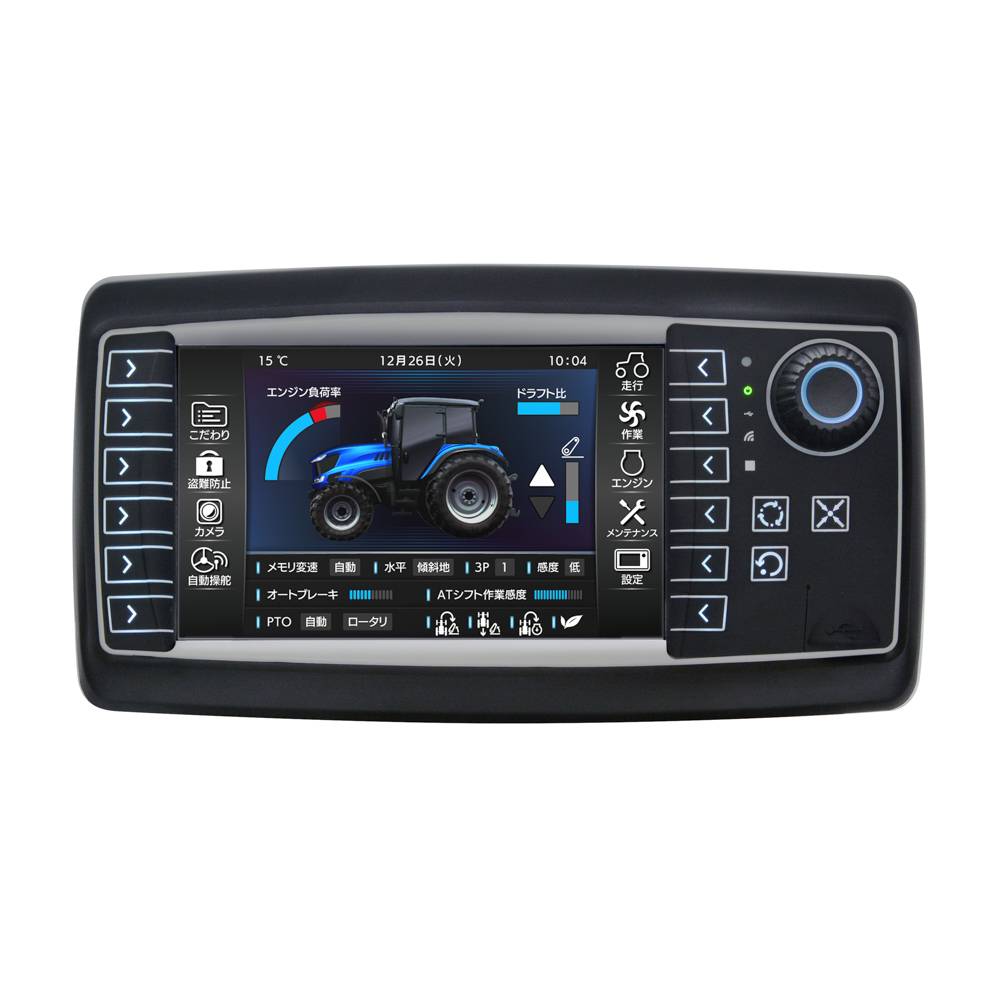
―― さて、今改めて「IMLT®」で弊社のユニバーサルデザインフォント「UD角ゴ_ラージ」をご採用頂いたプロセスを振り返って頂けますでしょうか。
鈴木さん:当初トラクタ操作端末「IMLT®」の使い方として、運転時に画面を一瞬だけ確認することを想定していました。そのため、瞬時に情報を正しく伝えられるフォントが必要でした。また、7 インチの画面に可能な限り多くの情報を表示したいという必要性もでてきたため、次第にUD フォントの優位性が高まってきました。さらにトラクタ操作端末に表示するためには組み込みフォントでなくてはならないことが分かり、弊社ではトラクタ操作端末への組み込みフォント搭載が初めての経験でしたので、いろいろと手探りで探して、当時数社のフォントメーカーに相談させて頂きました。
―― 他のフォントメーカー様にもご相談されていた中で、弊社をご選択頂いた理由はどこにあるのでしょうか?
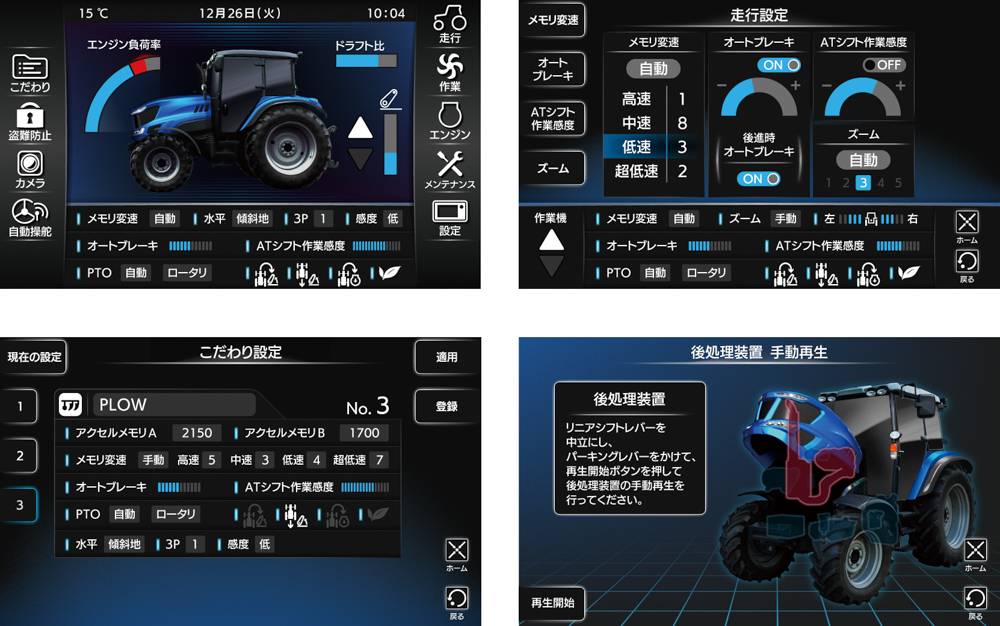
―― 御社のご希望に寄り添えたことは嬉しい限りです!ここからは、フォントのデザイン視点でお話を伺いたいと思います。先ずは、ユニバーサルデザイン(UD)のコンセプトを持ったフォント自体はご存知でしたでしょうか?
鈴木さん:ユニバーサルデザイン(UD)フォントの存在自体は認識していました。例えば、弊社の印刷物などで他社のUDフォントを実際に使用していました。
―― 既に他のフォントメーカー様のUDフォントを使用されていたなかで、弊社の「UD角ゴ_ラージ」をご採用頂いた理由はどこにあるのでしょうか?
鈴木さん:(トラクタ操作端末の)ディスプレイの解像度は、実はそこまで高精度なものではないんです。ディスプレイでは文字が荒れることが多い中で、「UD角ゴ_ラージ」は綺麗にはっきり見えるところが良いなと感じました。文字がしっかり読めるからこそ、ディスプレイに情報をより多く表示することができます。ふところが広く、曲線も美しいといった現代的な佇まいを感じさせながら、「分かりやすくて格好良い」という社内の評判が最後の決め手となりました。
―― UDフォントの基本的な特長である「可読性」「視認性」「判別性」の高さに加えて、弊社独自の観点である「美感性」を備えた「UD角ゴ_ラージ」の本質を見事に捉えて頂いています!
鈴木さん:フォントメーカー数社からフォントをお借りして、ディスプレイに表示して検証を行ったときに、「UD角ゴ_ラージ」を打ち込んで「これいい!」と(笑)。自身の感性に響きましたね。フォントそのものに心地よさと親しみやすさがあるため、お客様にもその心地よさは伝わっているだろうと感じています。
変化の大きい農業の世界を「骨太で息の長いデザイン」で支えたい!
―― 御社も2025年に創立100周年を迎えられますが、農業の世界も最近は特に大きく変貌を遂げているとお伺いしています。農業の世界で、いまどのような変化が起こっているのでしょうか?
鈴木さん:前提として、お客様が先ず変化していってますね。日本国内においては、農業従事者の高齢化が一層加速しています。それを背景に、農地の集約・大規模化がトレンドとなっており、そのプロセスで担い手農家と言われる若手や法人も多く参入してきています。
技術面に目を向けると、農業就業人口の減少に伴う作業の効率化・省力化でしょうか。具体的には、大規模経営ではAIやデータを活用したスマート農業が盛んになってきています。例えば、人が見回る代わりにドローンを飛ばして、撮影した画像の色から稲の生育具合をAIが判断して、水や肥料を調整する手法や、人工衛星の画像からお米の味の決め手であるタンパク質含有量を把握して、最適な収穫時期を決定する手法が普及レベルにきています。農業のやり方自体が大きく変わってきていることを感じます。
―― なるほど。因みに、御社のこの領域における最新の取り組みを教えてください。
鈴木さん:弊社では「可変施肥田植機」を販売しております。肥料を撒きながら田植えをするのが一般的になってきていますが、「可変施肥田植機」はリアルタイムセンシング技術で土壌の肥沃度合いを調べ、肥料を田んぼのどこにどれくらい撒くか最適化しながら田植えをします。そうすることで稲の倒伏を防ぎ、品質の安定したおいしいお米になります。
―― ご教示ありがとうございます。最後に、農業を取り巻く環境の変化に適応され、業界のフロントランナーとして走り続ける御社のデザイナーとして、鈴木さんの「矜持」をお聞かせください!
鈴木さん:農機は何十年と使い続けて下さるお客様も多くいらっしゃいますので、「骨太で息の長いデザイン」を常に心がけています。農機の世界でも新しい機能や操作が次々に出てきますが、特にUIデザインにおいては、見た目にしても、操作感にしても素直に入ってくるもの、本当に使いやすいと言っていただけるものを作り続けたい。これからも農業と農家のお客様に寄り添って、お客様の未来が広がるような製品を作り続けていきたいですね。
今回、取材を進めて行く中で、鈴木さんがプロダクトデザイナーを目指した「原点」をお伺いしました。
原体験として、福井の実家に田んぼがあり、農機具に触れる機会が身近に有ったとのこと。鈴木さんが幼い頃、農業に携わっていたおじいさんが田植えをしているときに「何となくワクワクしながら」田植機に触れていたことが、ずっと記憶に残っていたそうです。
幼少の頃は漫画を描くのが好きだった少年が、高校生の頃には工業製品のデザインに興味を抱き、静岡の大学でプロダクトデザインを専攻。就職活動では農機メーカーに絞って活動を続け、井関農機様に入社したという、大変興味深いお話を聞くことが出来ました。
「身近な人で農機メーカーに行った人は誰もいないし、誰もいないところで新しいことにチャレンジしたかった」(鈴木さん)
自身の感覚に忠実に従い、就職するまで一度も訪れたことのなかった四国の企業での挑戦を決めた鈴木さん。その飄々とした雰囲気とは裏腹に、確固たる芯を持ったプロダクトデザイナーであることを再認識させられました。
「新しい道具があると、生活がより便利になるし、豊かになるという価値の提供が出来る。新しいプロダクトをどんどん生み出し、それを使いやすくて魅力的なものに仕上げていくところで活躍していきたい」と語る鈴木さんの傍らに、今後も「UD角ゴ_ラージ」を中心とした弊社フォントが寄り添っていけたら、と心から願う取材となりました。